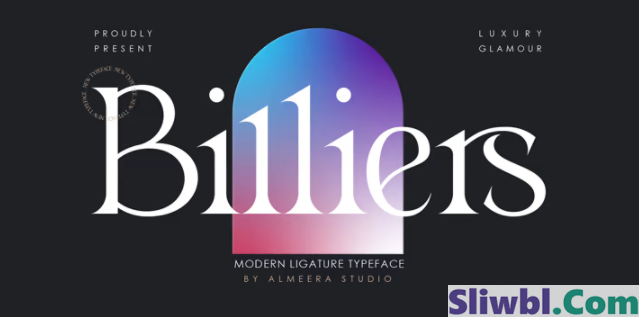
Представляем новый современный шрифт Billiers!!!
Billiers - это роскошный и гламурный шрифт с засечками. Этот шрифт одновременно современный и ностальгический и отлично подходит для логотипов, журналов, социальных сетей. Они уже подобраны и готовы к использованию для вашего следующего дизайна!
Для тех из вас, кто нуждается в элегантном, стильном, шикарном и современном дизайне, этот шрифт создан для вас!
Идеально подходит для редакционных проектов, дизайна логотипов, брендинга одежды, упаковки товаров, заголовков журналов или просто как стильное наложение текста на любое фоновое изображение.